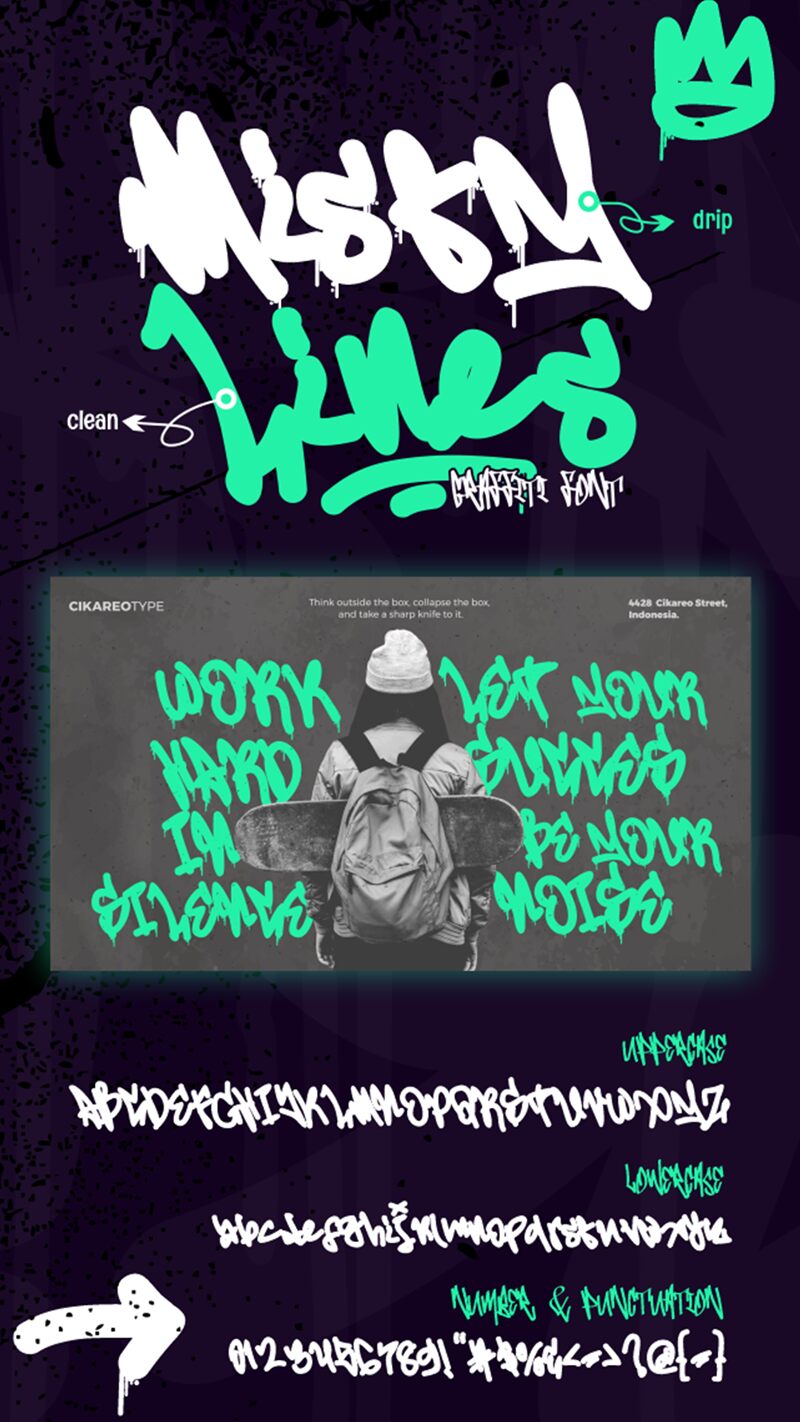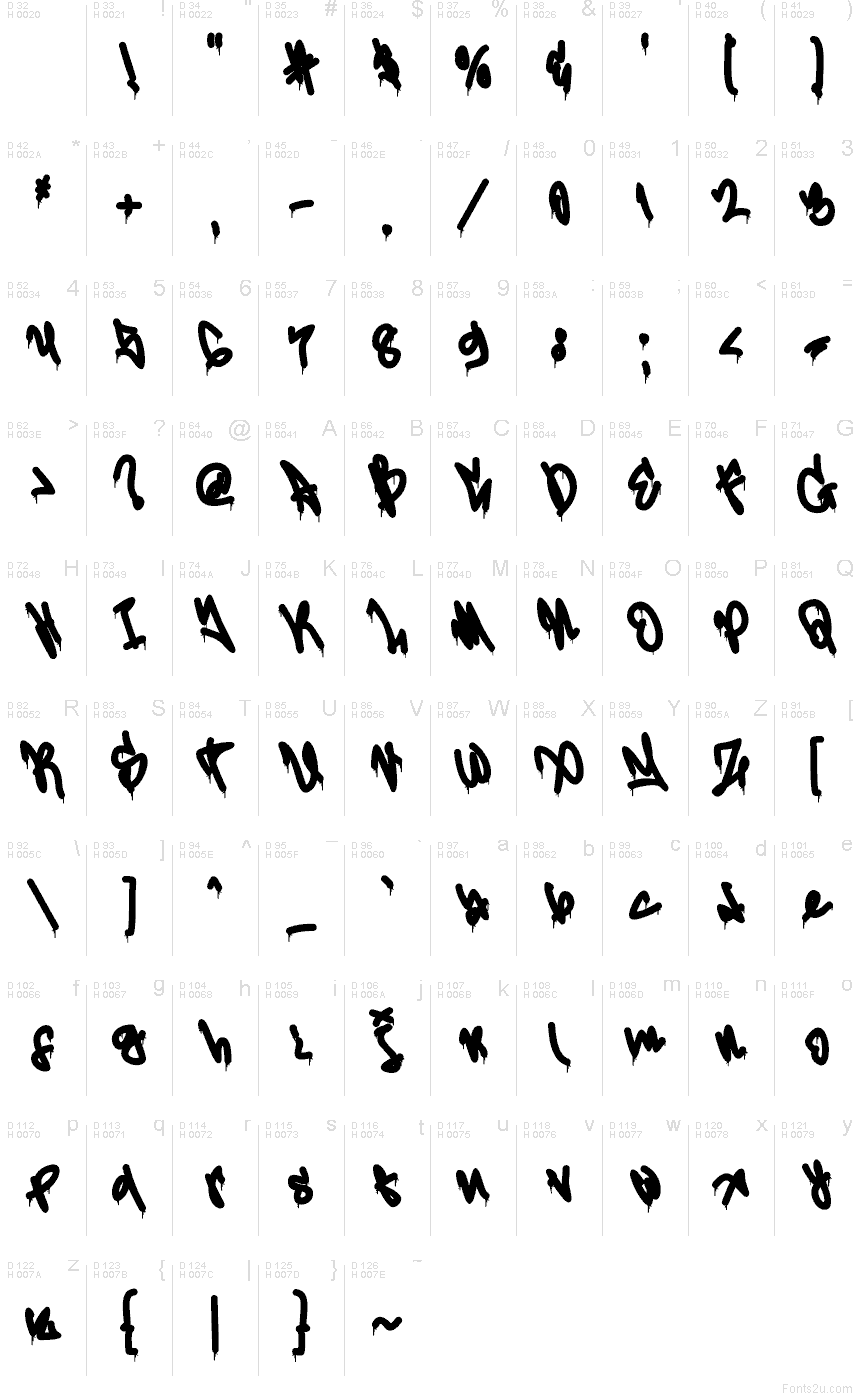
Misty Lines Drip
Misty Lines Drip, creata da Muhammad Panji Ramdhani di Figuree Studio, schizza sulla pagina come vernice fresca stesa rapidamente sul cemento: tratti irregolari, macchie corpose e lunghe colature che trasmettono un senso di autentico e selvaggio. È un font graffiti gratuito che, grazie al suo ritmo caotico e allo spessore variabile, infonde un'immediata energia urban ai tuoi design senza bisogno di texture o effetti aggiuntivi.
Usa Misty Lines Drip su copertine di album, loghi skate e streetwear, titoli di poster, adesivi, anteprime YouTube, flyer di eventi e packaging dal carattere ribelle per dare più incisività al tuo messaggio. Lascia che le lettere respirino in grandi dimensioni e abbinale a un font sans serif condensato e pulito per le date o le informazioni secondarie, così da mantenere la leggibilità nonostante il caos visivo. Questo font gratuito è perfetto quando cerchi attitudine, movimento e un tocco grunge.